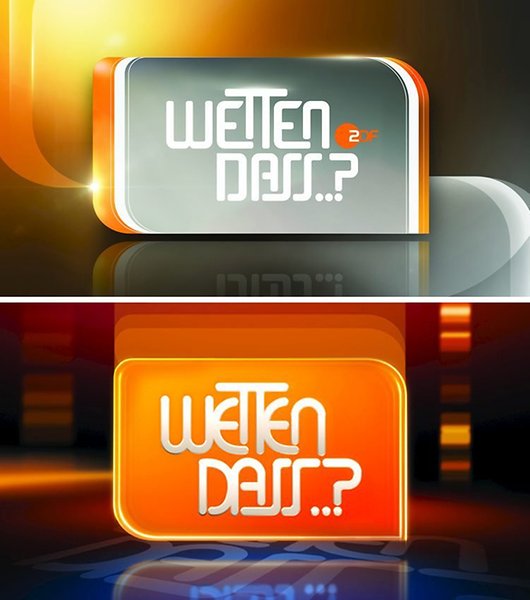
Wetten dass ..?
Das man nicht zu viel verändern wollte ist verständlich, die Farben sind ja auch etwas moderner (modischer?), aber die Schrift, finde ich, hat voll verloren. Das ist nur eckiger und dadurch technischer und m. E. unsympathischer, gerade mit dem Grau.
Sieht aus wie diese 80er-Jahre-Computerfonts. Passt irgendwie nicht.
Also genau betrachtet war schon das alte Logo nicht besonders frisch. Aber das neue wirkt tatsächlich noch muffiger.
Außerdem hat sich nun ein Rechtschreibfehler eingeschlichen: Es fehlt das Leerzeichen vor den Auslassungspunkten. (Ja, gut, vorher war’s auch falsch, weil’s nur zwei statt drei Punkte waren. Also lassen wir’s als gestalterische Freiheit durchgehen.)
Typografisch doch ein sichtbarer Fortschritt.
Dann findest Du also diese Willkür allein bei den Buchstabenabständen gelungener? Da überschneiden sie sich mal, dann doch lieber so ein Art Kissing, oder ganz listig die knappen Abstände der abgerundeten Ecken…
Da ist der neue Entwurf um Welten schlüssiger und auch stimmiger.
Gelungener? Weder das eine noch das andere ist überhaupt gelungen, wenn du es satztechnisch betrachtest. Beide sind aber Logos, da gelten – wenn überhaupt – ganz andere Regeln. Das alte war harmonischer, verbundener, zusammengehöriger, kompakter, eben eine Einheit. Das neue ist gesetzt, unverbunden, technisch, seelenlos.
Das Thema haben wir ja auch schon häufiger hier im Forum diskutiert: Normalerweise hat neues Führungspersonal das dringende Bedürfnis, neuen Wind in die Bude bringen. Und wie geht das am besten? Genau: mit einem neuen Logo! Auch wenn das alte noch gar nicht kaputt war … ;-)
Das Redesign erinnert mich an das "neue" Logo vom Arbeitsamt. Da musste wohl im Freundes-/Verwandtenkreis der vergebenen Kreise mal eine Wohltat verschenkt werden...
Ist doch ein logischer Zeitpunkt, das Outfit ein wenig aufzufrischen. Wird auch für Studio/Bühne gelten, on air sowieso, wird auch inhaltlich die ein oder andere Korrektur geben ohne daß man die Sendung neu erfinden wollte.
Ist doch ein logischer Zeitpunkt, das Outfit ein wenig aufzufrischen. …
Dem widerspricht auch niemand. Nur ist das Ergebnis halt nicht gelungen. Oder sogar misslungen ;-)
Ah. Bei Logos interessiert in der Regel aber eher das Ergebnis, weniger die Intention. Das eine bekommt die Welt nämlich mit, die andere hingegen nicht.
Dem widerspricht auch niemand. Nur ist das Ergebnis halt nicht gelungen. Oder sogar misslungen ;-)
gemach. ich finde das neue logo nicht misslungen und auch keinen rückschritt im vergleich zu dem alten. das bisherige sendungslogo hat mich an das zdf-senderlogo aus den späten achtzigern erinnert und sich auch dementsprechend altmodisch angefühlt. außerdem fand ich die kombination aus sonst eckigen, aber rund gezeichneten und sonst runden, aber eckig gezeichneten buchstaben eher krude als gemütlich. da erscheint es mir naheliegender und auch optisch überzeugender, die ineinander verschränkten buchstaben einem raster folgen zu lassen. die gleichsetzung von eckigen, technisch wirkenden formen mit einer ›seelenlosen‹ anmutung geht mir jedenfalls zu weit. dass grau (oder silber) als, neben orange, zweiter für das zdf wichtiger farbe mehr raum gelassen wird, leuchtet mir dafür ein – insbesondere wenn man die sendung etwas weniger bieder erscheinen lassen will. man muss sich das ohnehin mal on air und in der bühnendekoration ansehen. ob das gesamtpaket dann eher neue, jüngere zuschauer anlockt oder bisherige, alte abschreckt, wird sich ja im oktober zeigen.
Neben der nun doch strukturierteren Kombination der Buchstaben find ich auch einen deutlichen Fortschritt daß die Buchstaben selber von den ganzen Effekten entrümpelt und letztere ins Umfeld verlagert wurden. Die Farbkombi find ich sogar gelungen.
… deutlichen Fortschritt daß die Buchstaben selber von den ganzen Effekten entrümpelt …
Welche Effekte meinst du?
Kleiner Tipp am Rande: hinschaun.
Bei ein bisschen Schatten als "von den ganzen Effekten" zu sprechen halte ich aber für ein wenig übertrieben. Noch wissen wir ja gar nicht, wie sich das neue Logo in der dritten und vierten Dimension verhält, da könnten diese ganzen Effekte durchaus wieder eingesetzt werden. Für meinen Geschmack ist und bleibt das neue Logo keine Verbesserung, nur eine Veränderung.